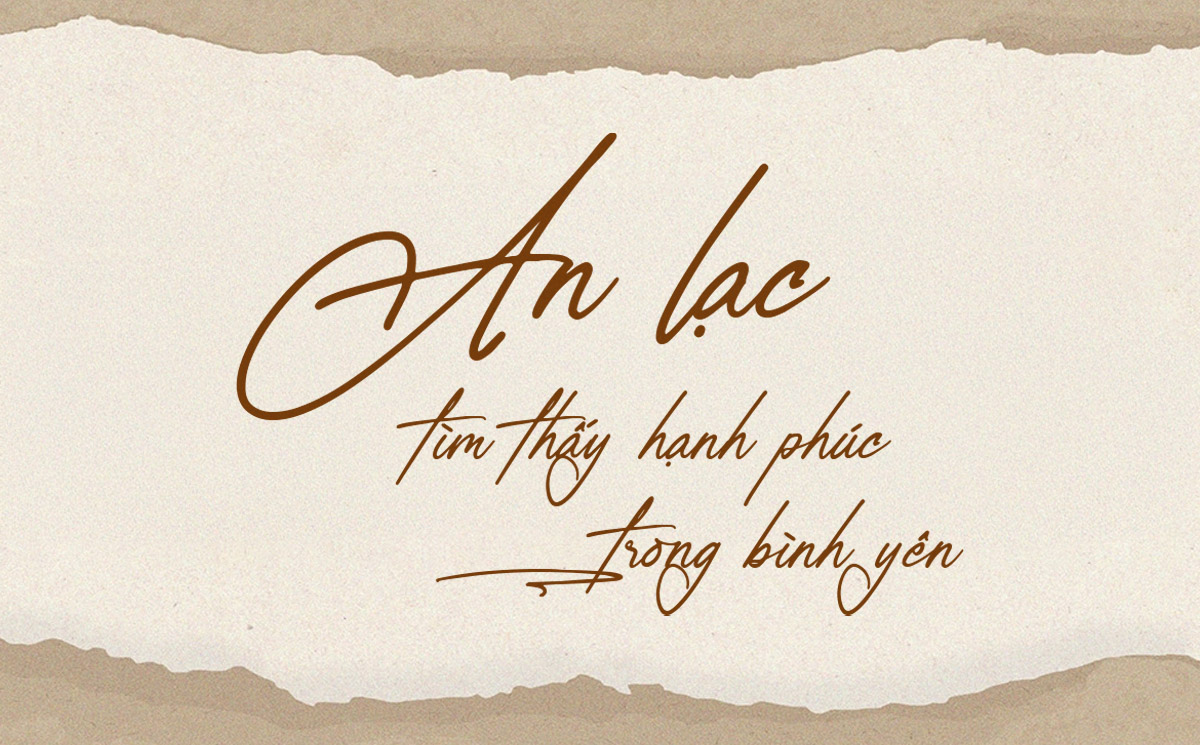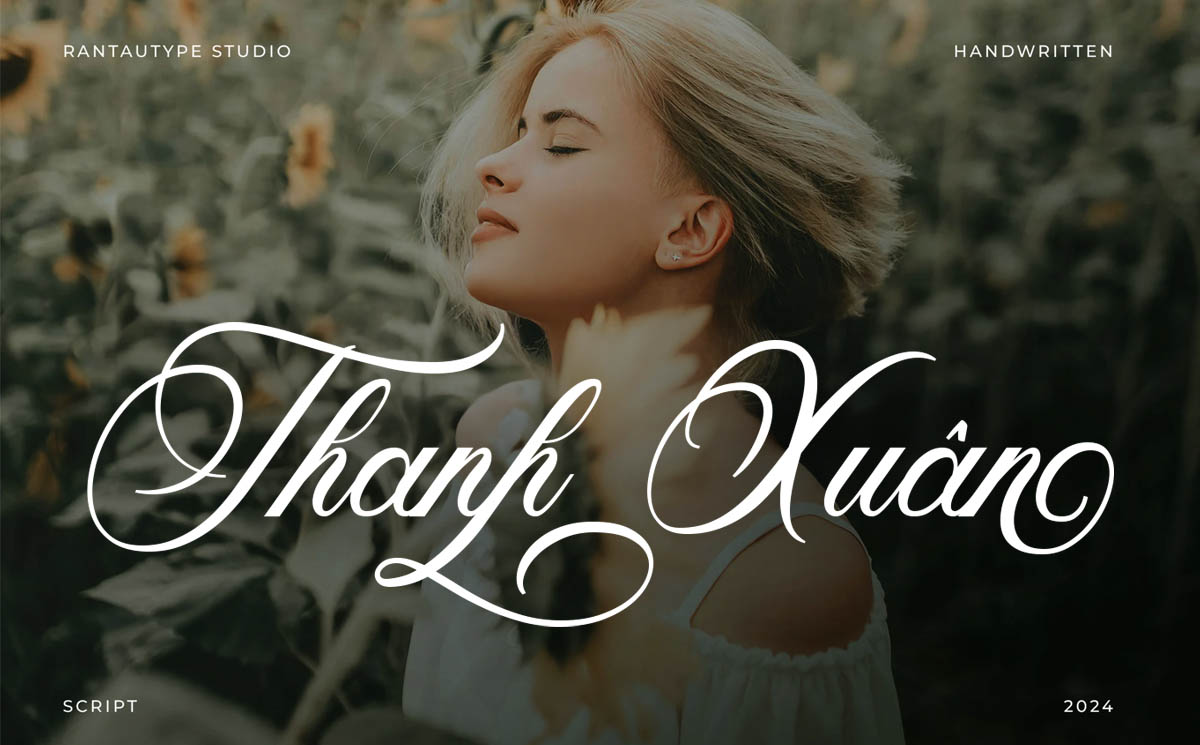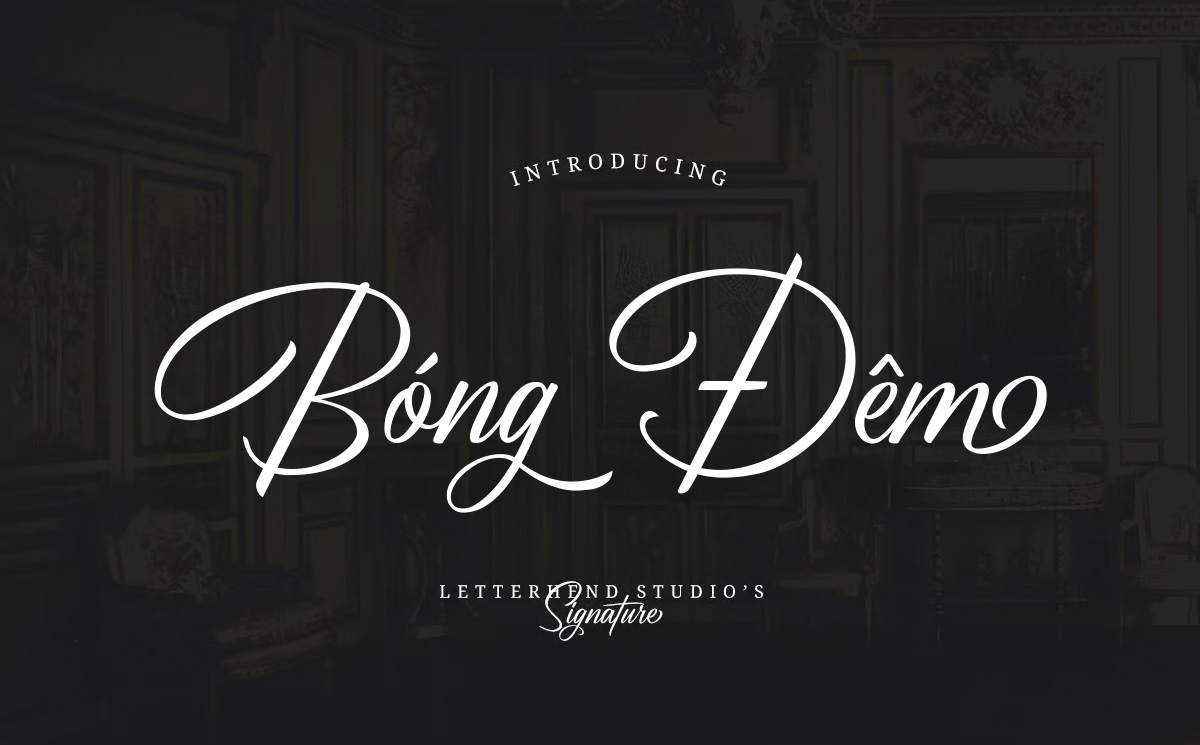
Font chữ cho shop handmade, Etsy, thiệp cảm ơn và bao bì thủ công
Gợi ý 18 font TH Việt hóa cho shop handmade, Etsy, thiệp cảm ơn, sticker và bao bì thủ công.
Shop handmade thường bán nhiều hơn một món đồ: họ bán cảm giác được làm thủ công, được chăm chút và có dấu ấn cá nhân. Vì vậy font chữ trên logo, sticker, thiệp cảm ơn và bao bì cần mềm, gần gũi, nhưng vẫn phải đọc rõ tiếng Việt.
Bài viết này gợi ý 18 font TH Việt hóa phù hợp cho shop handmade, Etsy, thiệp cảm ơn, sticker, tag giấy và bao bì thủ công. Mỗi font có link tải và ảnh preview để bạn test nhanh với tên shop thật.
Cách chọn font cho shop handmade và Etsy
Với Etsy hoặc shop handmade nhỏ, font nên thể hiện được chất liệu sản phẩm: len móc, nến thơm, xà phòng, hoa khô, gốm, phụ kiện, bánh handmade hay quà tặng. Tuy nhiên, đừng dùng font script cho mọi thứ. Tên shop, lời cảm ơn và slogan có thể dùng chữ viết tay; thông tin sản phẩm, thành phần, size, mã hàng và hướng dẫn bảo quản nên dùng font phụ rõ ràng.
Nếu bao bì in trên giấy kraft, sticker nhỏ hoặc tag treo, hãy kiểm tra dấu tiếng Việt ở kích thước thật. Nét quá mảnh hoặc quá uốn có thể đẹp trên màn hình nhưng khó đọc khi in nhỏ. Một hệ font hiệu quả thường gồm một font chữ ký cho điểm nhấn, một font handwriting thân thiện và một font sans-serif phụ cho nội dung dài.
Gợi ý font TH Việt hóa cho handmade, thiệp cảm ơn và bao bì thủ công
1. TH Bengoda
TH Bengoda phù hợp với thiệp cảm ơn, chữ ký thương hiệu, sticker “made with love” và lời nhắn nhỏ trong hộp. Khi dùng cho shop handmade, bạn có thể đặt font ở logo chữ, thank-you card, sticker, tem niêm phong, tag giấy hoặc headline ảnh sản phẩm. Với phần thông tin chi tiết, hãy phối cùng font phụ rõ ràng để khách đọc nhanh.
2. TH Histerm
TH Histerm phù hợp với shop handmade nữ tính, candle, soap, quà tặng và bao bì cần cảm giác mềm mại. Khi dùng cho shop handmade, bạn có thể đặt font ở logo chữ, thank-you card, sticker, tem niêm phong, tag giấy hoặc headline ảnh sản phẩm. Với phần thông tin chi tiết, hãy phối cùng font phụ rõ ràng để khách đọc nhanh.
3. TH Jalliya
TH Jalliya phù hợp với bộ nhận diện linh hoạt cho thank-you card, label, tag giấy và ảnh bìa Etsy. Khi dùng cho shop handmade, bạn có thể đặt font ở logo chữ, thank-you card, sticker, tem niêm phong, tag giấy hoặc headline ảnh sản phẩm. Với phần thông tin chi tiết, hãy phối cùng font phụ rõ ràng để khách đọc nhanh.
4. TH Bramostia
TH Bramostia phù hợp với chữ ký nét mảnh, phù hợp card cảm ơn, chữ ký founder và sticker handmade cao cấp. Khi dùng cho shop handmade, bạn có thể đặt font ở logo chữ, thank-you card, sticker, tem niêm phong, tag giấy hoặc headline ảnh sản phẩm. Với phần thông tin chi tiết, hãy phối cùng font phụ rõ ràng để khách đọc nhanh.
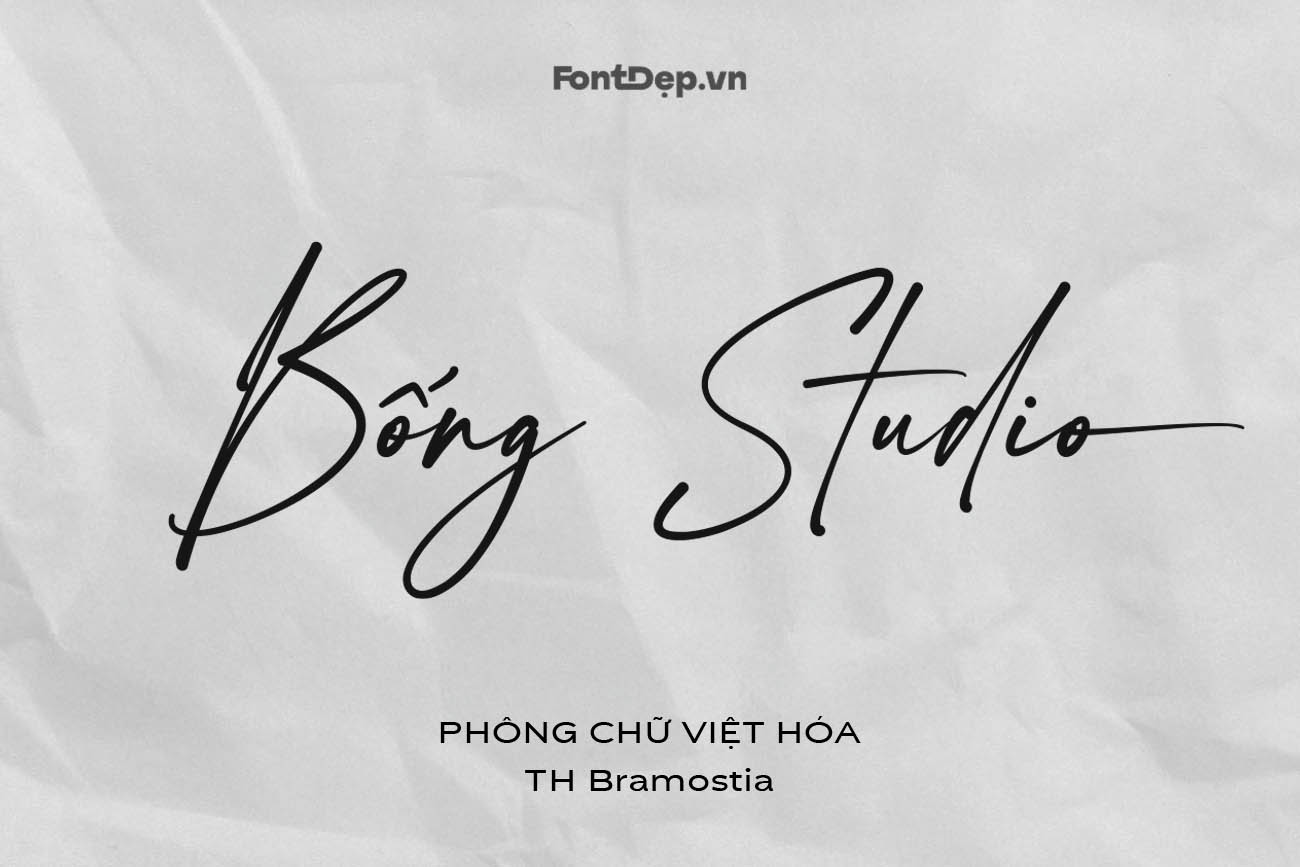
5. TH Mrattoos Regular
TH Mrattoos Regular phù hợp với logo chữ ngắn, tag quà, nhãn hộp nhỏ và các dòng chữ tạo cảm giác cá nhân. Khi dùng cho shop handmade, bạn có thể đặt font ở logo chữ, thank-you card, sticker, tem niêm phong, tag giấy hoặc headline ảnh sản phẩm. Với phần thông tin chi tiết, hãy phối cùng font phụ rõ ràng để khách đọc nhanh.
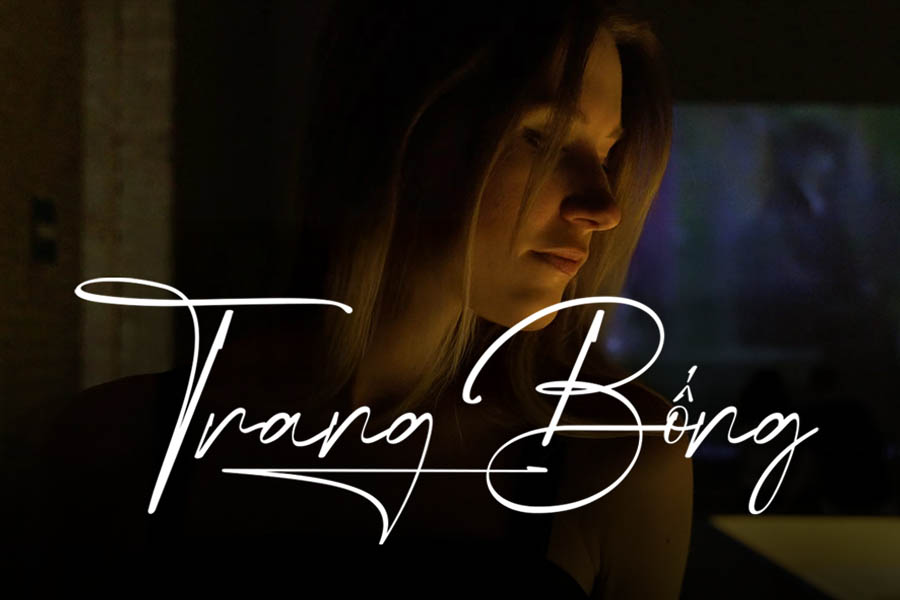
6. TH Bonitte
TH Bonitte phù hợp với shop handmade phong cách retro, tem dán, bao bì giấy kraft và postcard thủ công. Khi dùng cho shop handmade, bạn có thể đặt font ở logo chữ, thank-you card, sticker, tem niêm phong, tag giấy hoặc headline ảnh sản phẩm. Với phần thông tin chi tiết, hãy phối cùng font phụ rõ ràng để khách đọc nhanh.
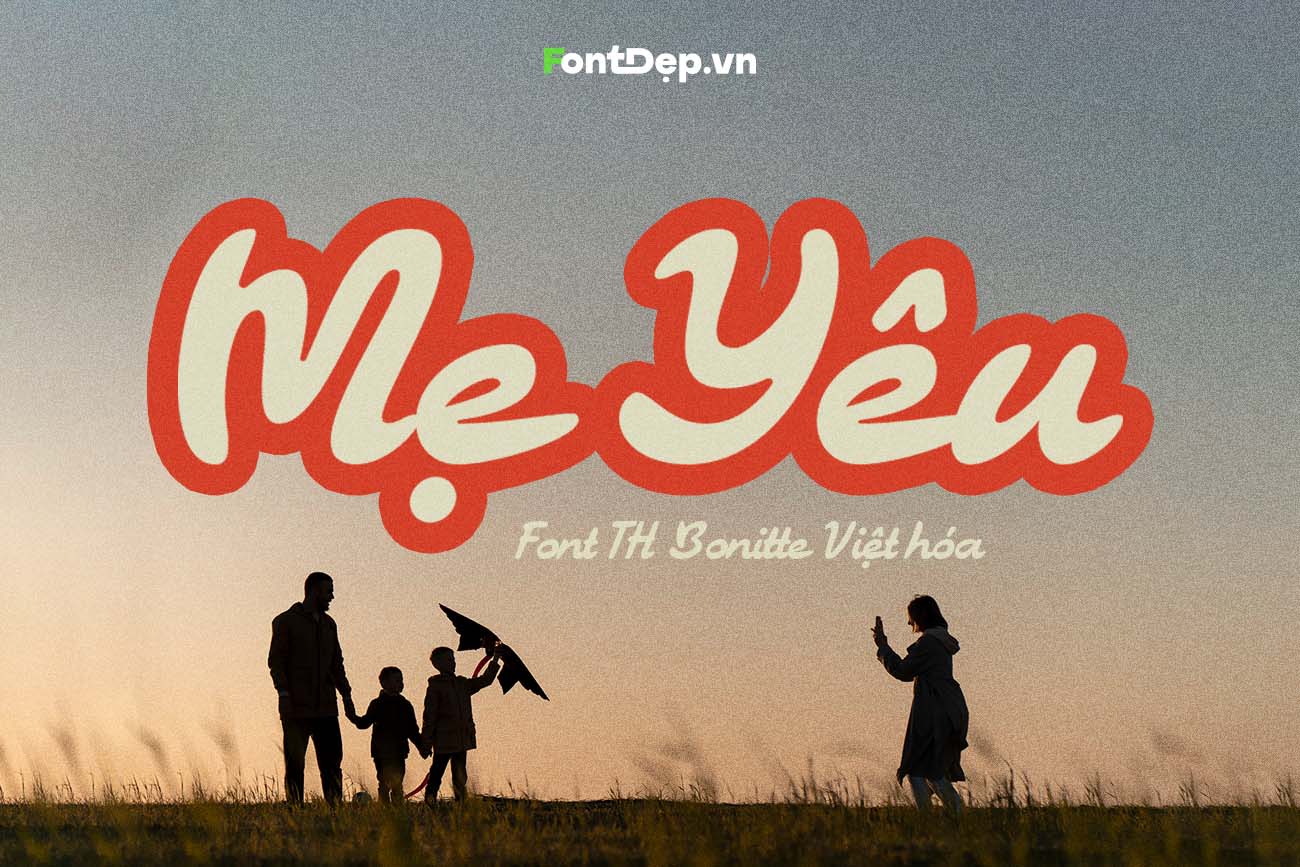
7. TH Victory Landera
TH Victory Landera phù hợp với thank-you card, chữ ký thương hiệu, label sản phẩm và bao bì gift set. Khi dùng cho shop handmade, bạn có thể đặt font ở logo chữ, thank-you card, sticker, tem niêm phong, tag giấy hoặc headline ảnh sản phẩm. Với phần thông tin chi tiết, hãy phối cùng font phụ rõ ràng để khách đọc nhanh.
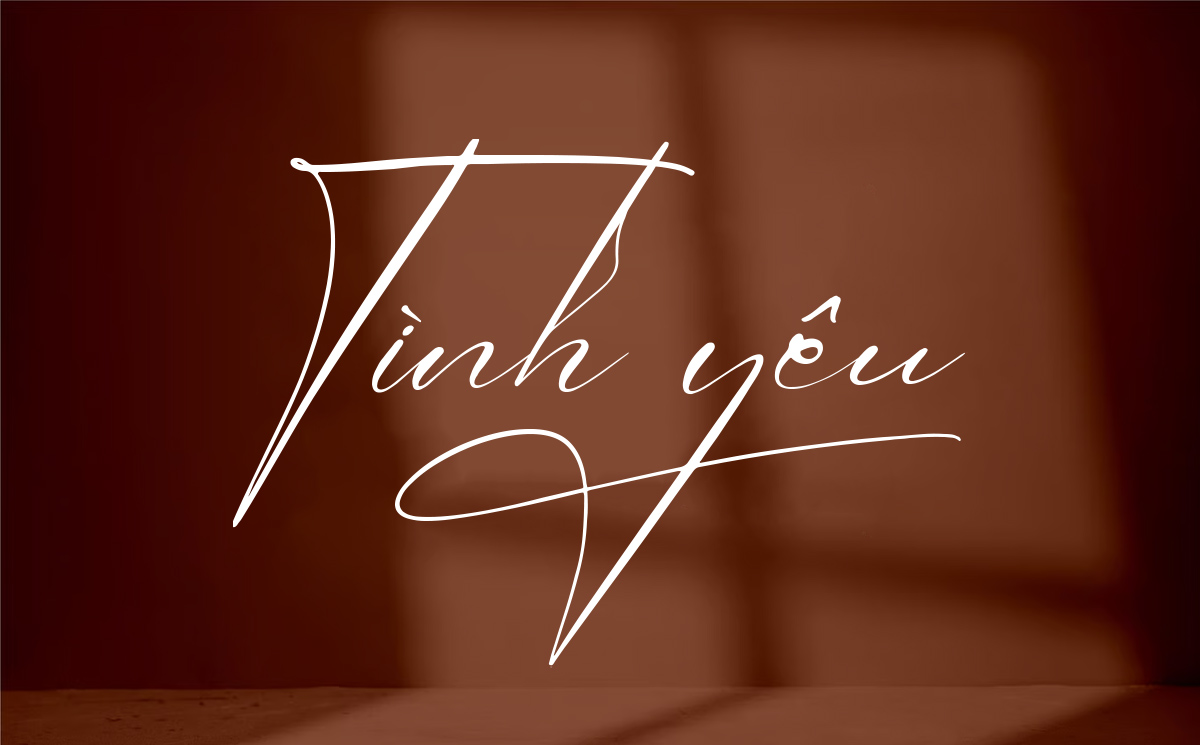
8. TH Buttain Regular
TH Buttain Regular phù hợp với dòng chữ nghiêng mềm, phù hợp nhãn hoa khô, thiệp nhỏ, voucher và quote trên ảnh sản phẩm. Khi dùng cho shop handmade, bạn có thể đặt font ở logo chữ, thank-you card, sticker, tem niêm phong, tag giấy hoặc headline ảnh sản phẩm. Với phần thông tin chi tiết, hãy phối cùng font phụ rõ ràng để khách đọc nhanh.
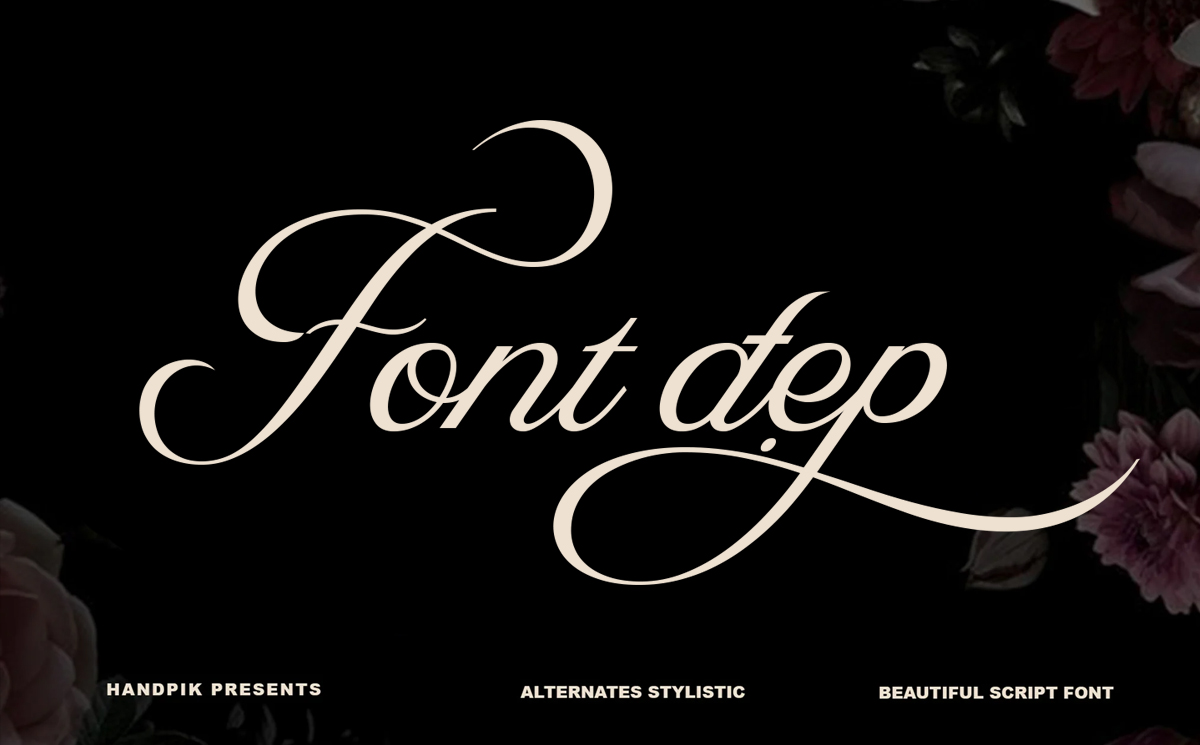
9. TH modernline
TH modernline phù hợp với logo phụ, chữ ký tự nhiên, sticker thank you và các điểm chạm cá nhân hóa. Khi dùng cho shop handmade, bạn có thể đặt font ở logo chữ, thank-you card, sticker, tem niêm phong, tag giấy hoặc headline ảnh sản phẩm. Với phần thông tin chi tiết, hãy phối cùng font phụ rõ ràng để khách đọc nhanh.
Gift box, thiệp cưới handmade và sản phẩm premium
Với gift box hoặc thiệp cưới handmade, TH Ganetha, TH Bengoda, TH Molahesta Italic, TH modernline và TH Victory Landera sẽ hợp hơn. Nhóm này tạo cảm giác cá nhân hóa, tinh tế và phù hợp với bao bì cao cấp.
Font handmade đẹp là font giúp khách cảm nhận được sự chăm chút, nhưng không làm thông tin bị rối. Hãy chọn một font viết tay cho cảm xúc, một font phụ để đọc rõ, rồi test trên sticker, thank-you card, ảnh Etsy và bao bì thật trước khi in hàng loạt.